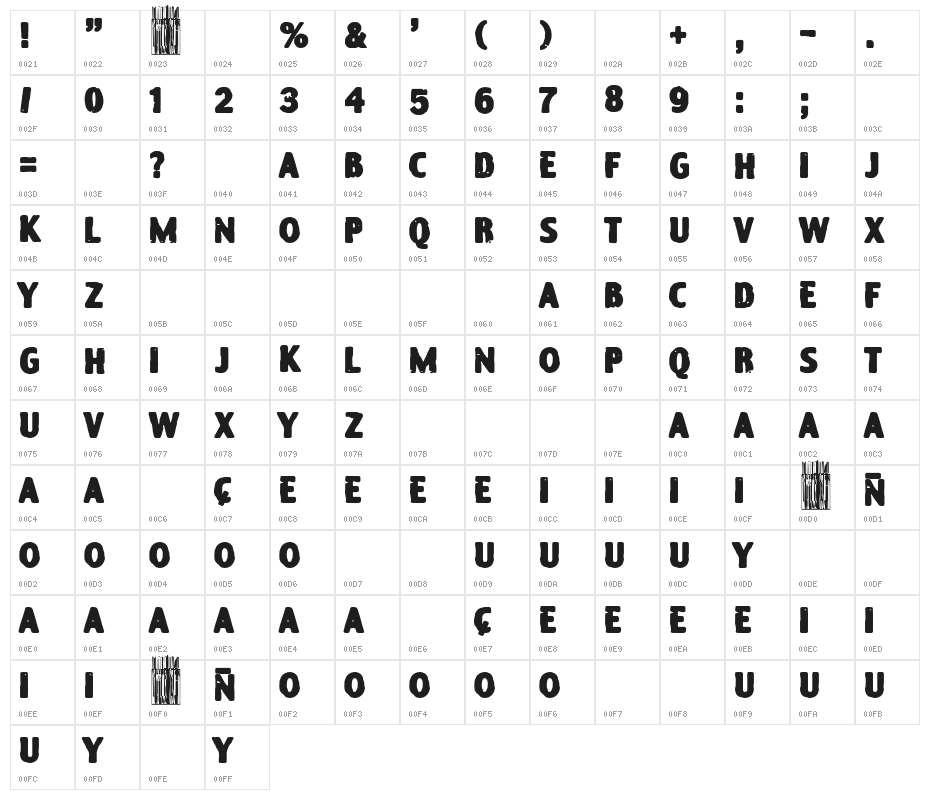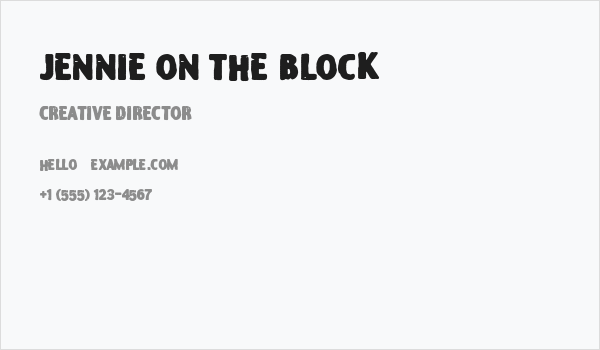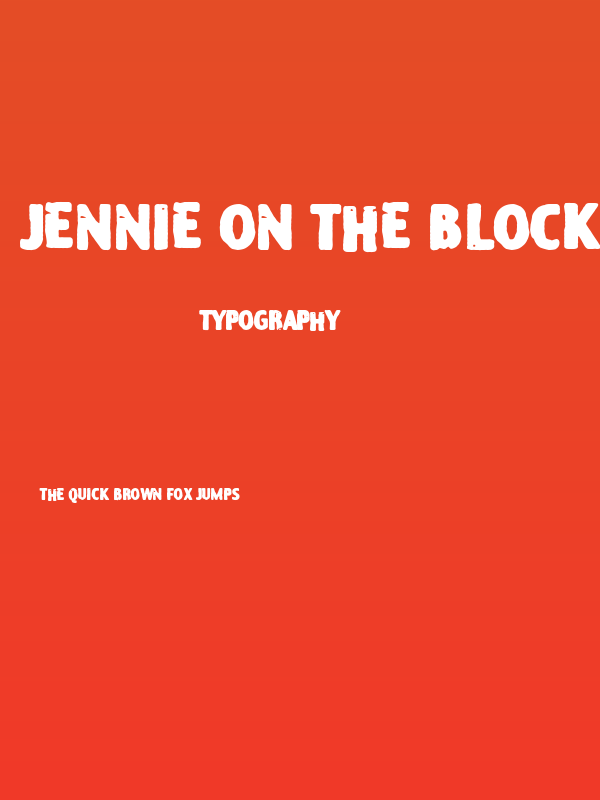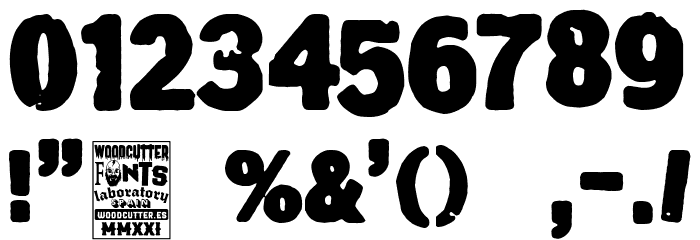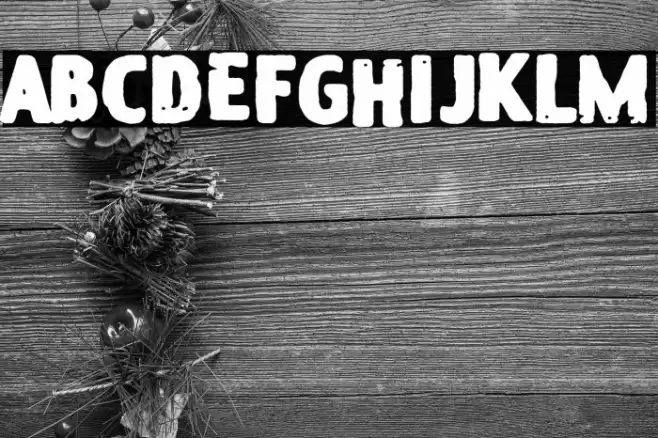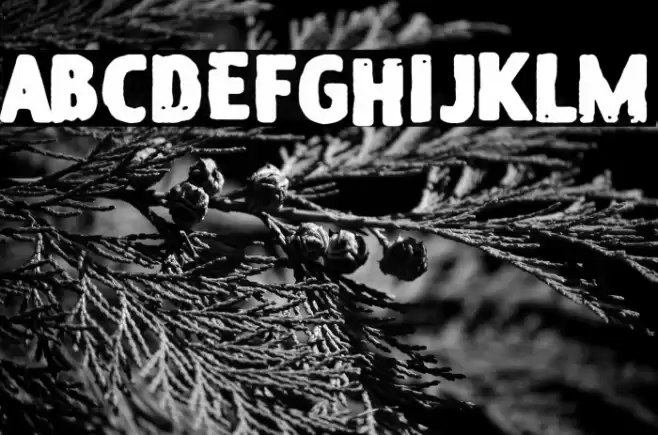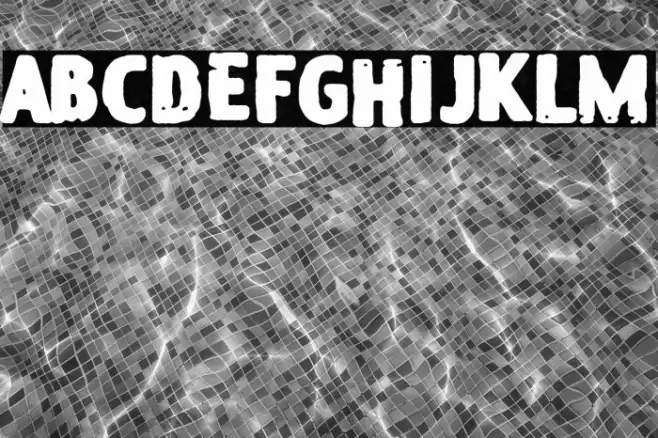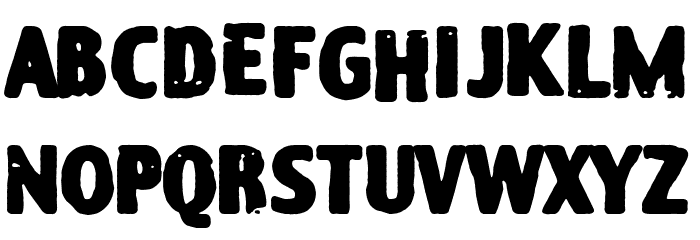
Jennie on the Block Font
| Kategorien | Retro |
| Gesamtstil | Vintage |
| Anwendungsfall | Logos, Posters, Branding |
| Vorgeschlagene Projekte | Perfect for posters, logos, branding, and any design requiring a bold, vintage aesthetic. |